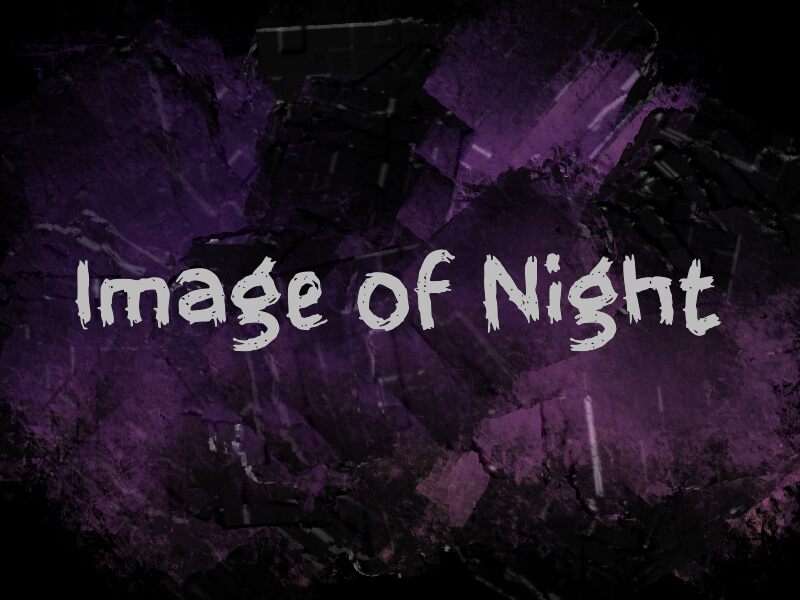
Image of Night
Image of Night di Wep è un font horror in stile pennellata gratuito, con lettere che sembrano sporche, gocciolanti e graffiate. I bordi irregolari e i tratti umidi e cadenti gli conferiscono un'atmosfera da slasher notturno, mentre le forme massicce mantengono la scritta audace e immediata, senza fronzoli.
Questo font gratuito è perfetto per locandine di film horror, volantini per eventi di Halloween, branding per attrazioni a tema, titoli di videogiochi e copertine di album dark, dove il tratto irregolare del pennello riesce a impostare subito la scena. Funziona bene anche per brevi intestazioni sui social o per l'apertura di capitoli, quando vuoi che le lettere sembrino disordinate e materiche, come se la vernice stesse ancora colando verso il basso.